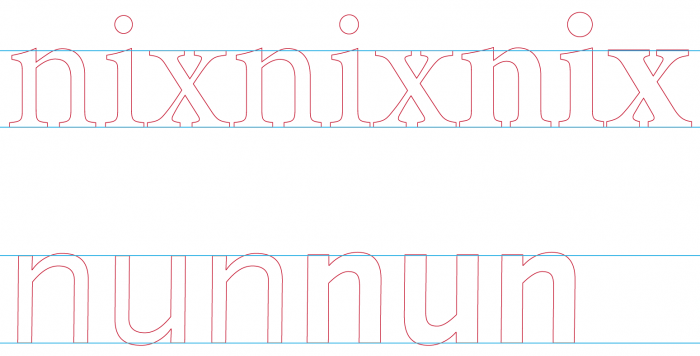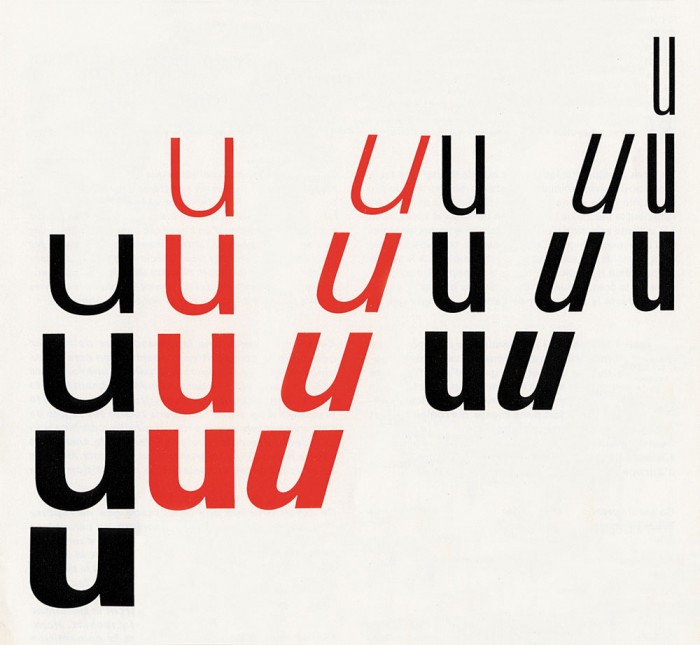
Entwicklung von Schriftschnitten (regular, bold, light): Welche Proportionen verwenden?
Ich habe einen Font im Schriftschnitt regular entwickelt. So weit so gut.
Jetzt möchte ich aber zusätzlich noch die Schriftschnitte Light und Bold entwickeln und frage mich, ob hierzu Regeln/Definitionen/Erfahrungen bzgl. der Proportionen/Größenverhältnisse gibt.
D.h. ist zum Beispiel ein Stamm/Strich eines Light-Schnittes nur halb so dick/breit wie der eines Regular-Schnittes? Noch dazu bei einer Antigua mit unterschiedlich breiten Stämmen ...
Wenn ja es Proportionen der Schriftschnitte zueinander gibt, wie verhalten sich diese rechnerisch.
Regular = 100% in der Breite des Stammes, aber Light = 80% und Bold = 120%?
Wie erfolgt die Ausrichtung der neuen Schnitte zum Regular-Schnitt?
Proportional gleich? -> D.h. eine Bold-Variante eines Zeichens in Regular "wächst" gleichmäßig nach innen und außen?
Die Versal-/X-höhen bleiben ja vermutlich unter den Schriftschnitten einer Schriftfamilie gleich. Aber wie sieht es mit der Dickte aus. Ist es erstrebenswert, dass die Dickte eines Zeichens bei unterschiedlichen Schriftschnitten gleichbleibt? Oder „darf“ ein Bold-Schnitt eines Zeichens im Verhältnis zum Regular-Schnitt in der Dickte zu legen?
#1 und #2: Notes on type design / Bold /
What exactly is a bold? It’s probably whatever you say it is, as long as it isn’t actually lighter than the regular weight. It is usually between two-fifths and two-thirds heavier.
#3: Notes on type design / Bold / Where?
Here are five versions of a bold letter u. … Second from the right is a letter with three fourths of the weight on the inside and one-fourth on the outside. That seems to be a popular choice.
#4: Ein Bold-Schnitt darf in der Dickte zulegen, ja tut das normalerweise auch, es sei denn es handelt sich um eine nichtproportionale Schrift, also eine Monospace. Die Versal-Höhe bleibt gleich, die X-Höhe kann sich durchaus unterscheiden.
In der Bleisatz-Walbaum von Berthold sind die halbfetten Gemeinen breiter als die mageren, aber die halbfetten Versalien sind schmaler als die mageren. Man macht eine Schrift also nicht allein dunkler durch Verbreiterung der schwarzen Linien, sondern auch durch Verschmälerung der weißen Flächen. »Fetter« heißt erst einmal nicht »breiter«, sondern »dunkler«.
Ist aber eine schöne Antwort für die Frage #3
Wie erfolgt die Ausrichtung der neuen Schnitte zum Regular-Schnitt?
Proportional gleich? -> D.h. eine Bold-Variante eines Zeichens in Regular "wächst" gleichmäßig nach innen und außen?
und wenn es bei der Bleisatz-Walbaum von Martin so gehalten ist – also Zuwachs bei den Versalien nach innen, bei den Gemeinen sowohl als auch, zeigt es ja auch ganz schön wie flexibel das gehandhabt werden kann.
In der Regel würde – s. Briem – eine Schrift, bei der alles zusätzliche »Gewicht«, also die Verdickung der Stämme, nach innen wandert, geschmälert bzw. condensed erscheinen.
#4: Ein Bold-Schnitt darf in der Dickte zulegen, ja tut das normalerweise auch, es sei denn es handelt sich um eine nichtproportionale Schrift, also eine Monospace. Die Versal-Höhe bleibt gleich, die X-Höhe kann sich durchaus unterscheiden.
Auch dazu noch eine Anmerkung: In der Arno (digital) sind die Versalien der fetteren Schnitte niedriger als die des gewöhnlichen Schnitts. In der Stempel-Garamond (digital) sind die fetten Versalien etwas höher als die mageren.
Tja, soviel zu absoluten Aussagen :nicken:
Leichte Schnitte fallen in der Regel optisch etwas größer aus als fette. Manche Schriftgestalter berücksichtigen das und gleichen entsprechend aus.  :nicken:
Und wie erklären wir jetzt dem jungen Mann designermohr, warum dieser optische Ausgleich bei Arno und Stempel Garamond jeweils unterschiedlich vorgenommen wurde :-?
Ich würde jetzt mal eingeschränkter formulieren, daß ein optischer Ausgleich in der Regel bei Versalien nicht vorgenommen wird, aber das es durchaus Usus ist, die x-Höhe entsprechend zu korrigieren … und habe mal bei Minion Pro und Syntax nachgeschaut. Bei beiden wird die x-Höhe der fetten Schnitte leicht angehoben, damit sie optisch mit den normalen Schnitten harmonieren (s. screenshot, ich hoffe es ist einigermassen zu sehen)
Tobias Frere-Jones hat übrigens auf seinem Blog eine schöne Artikelserie gestartet mit dem Titel Typeface Mechanics berührt jetzt zwar nicht direkt dein Thema aber vielleicht die nächste Ausgabe? ah, ja:
The entanglements of weight, width, and spacing happen at the same time, as do the predicaments inside each letter. But those come next.